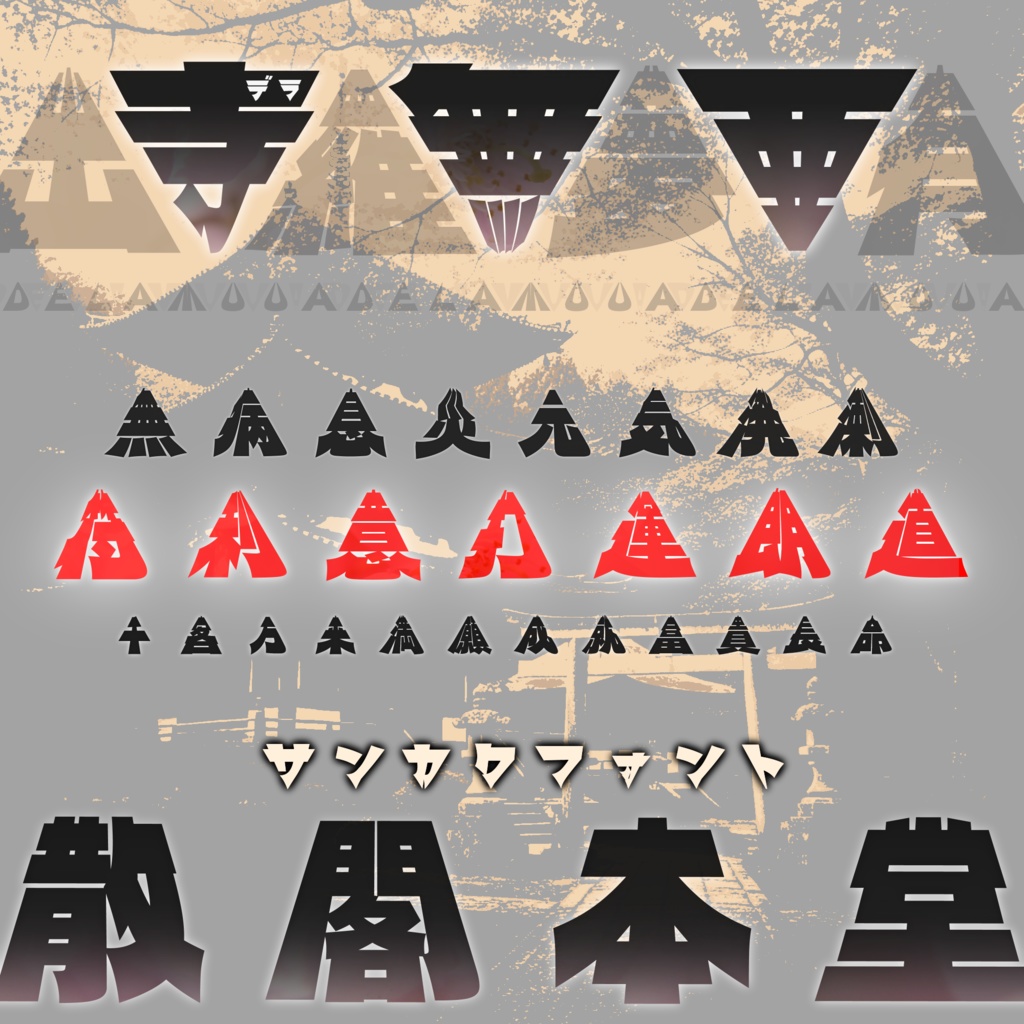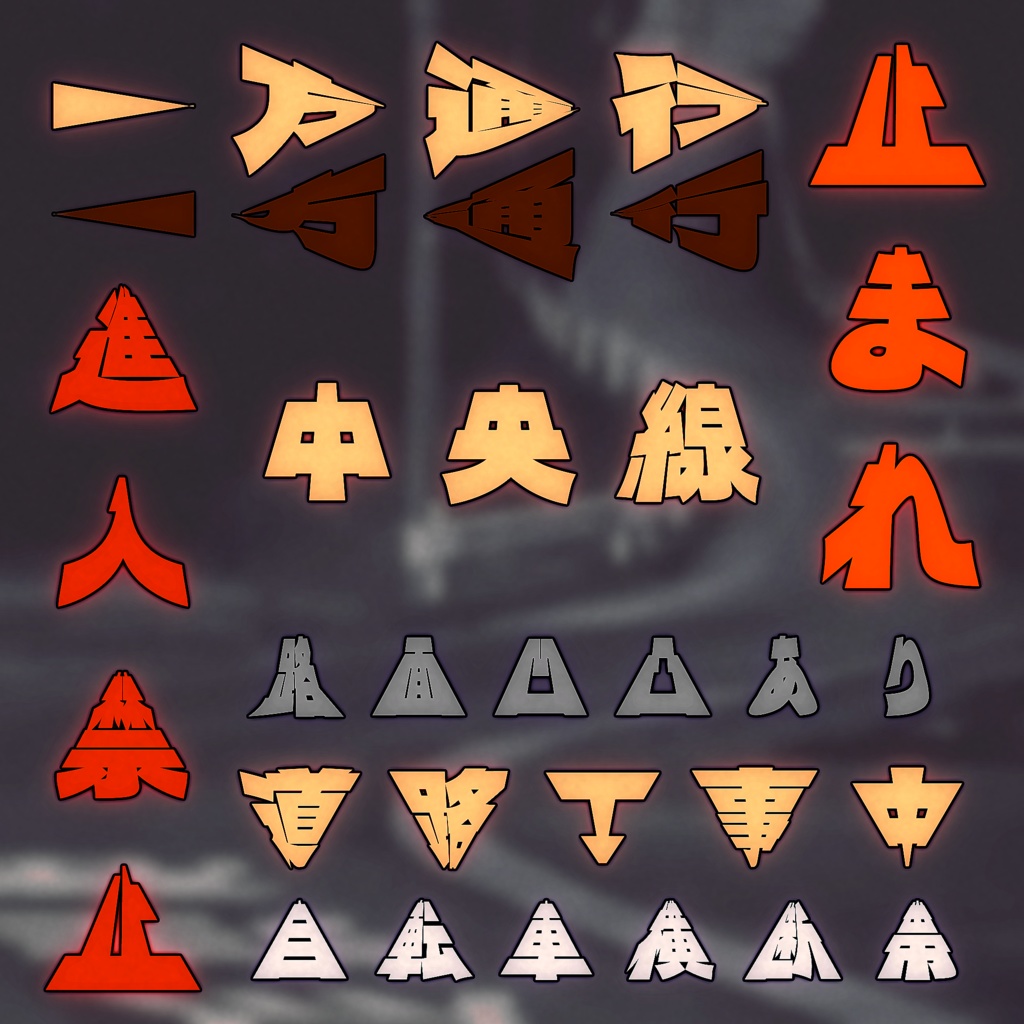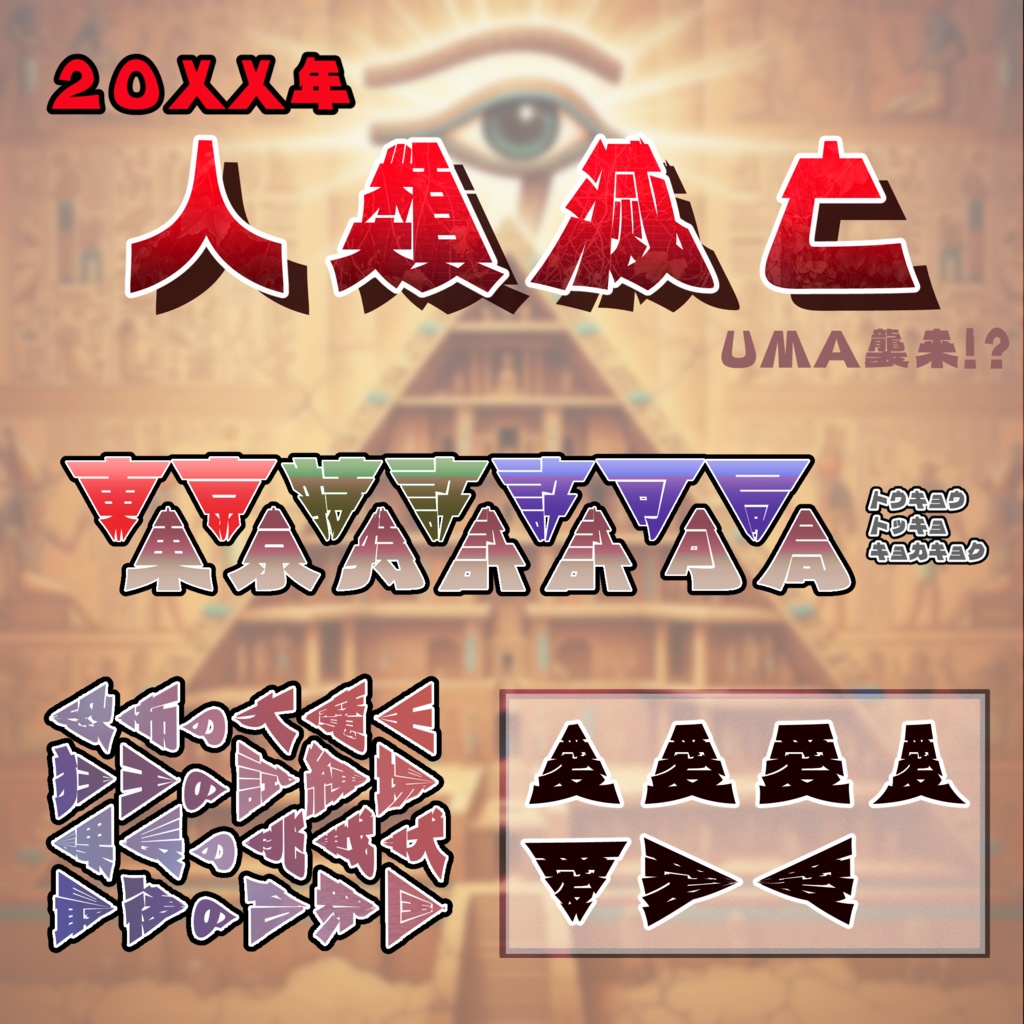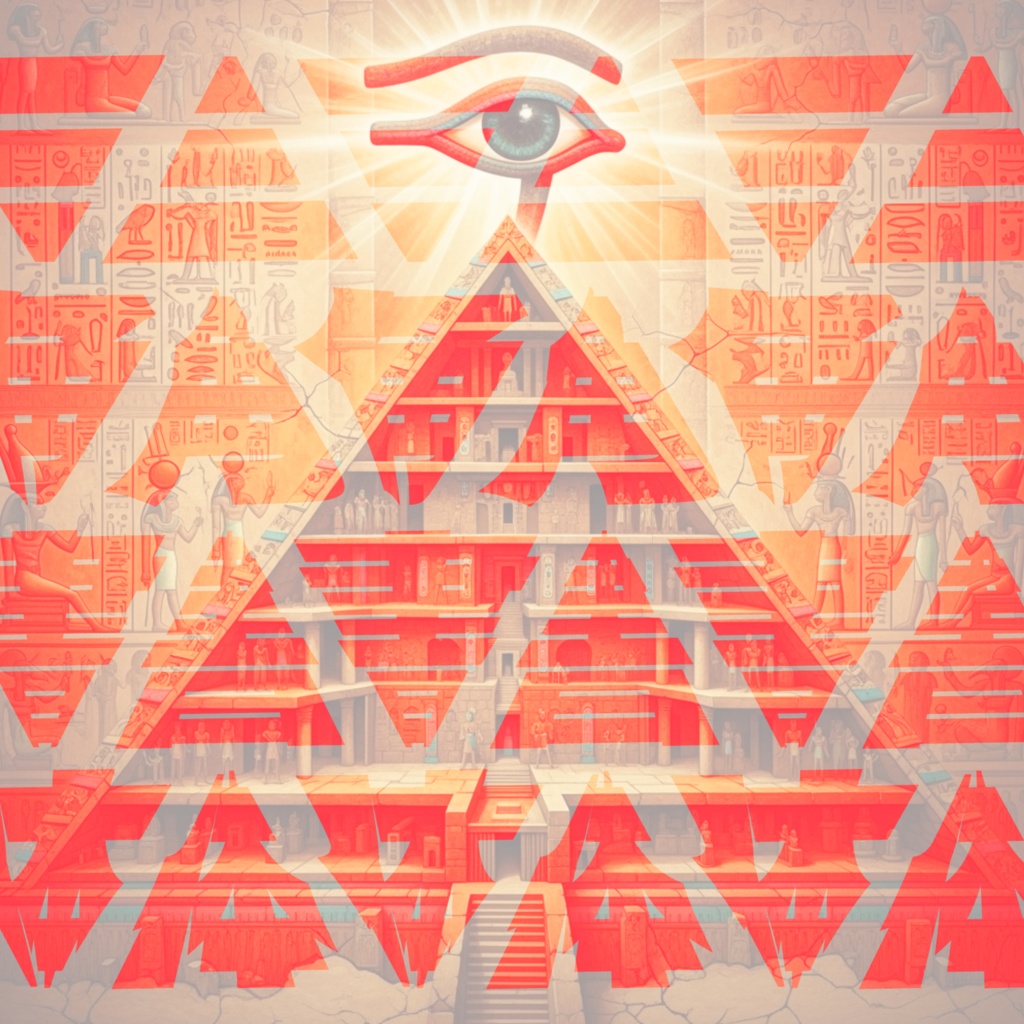
三角書体『デラ・ムーア』【フリーフォント】
『デラ・ムーア』(Dela-MuuA) 三角形が刻む、新たなインパクト。 シャープな三角形のシルエットが目を引く、デザイン向けのフォントです。
● デラ・ムーア 上 1 ● デラ・ムーア 上 2 ● デラ・ムーア 上 3 ● デラ・ムーア 上 4 ● デラ・ムーア 下 ● デラ・ムーア 左 ● デラ・ムーア 右 尖りの方向や鋭さが異なる、合計7種類のフォントを同梱。 「上1〜3」と「下」が使いやすくおすすめです。
本フォントは、オープンソースフォント 『デラゴシック』(Dela Gothic One) https://github.com/syakuzen/DelaGothic をベースに、独自の加工と調節を施して制作しました。素晴らしいフォントを公開してくださった制作者様に心より感謝申し上げます。 【ご使用上の注意点】 漢字のデザインを優先して制作したため、ひらがな、カタカナ、英数字などの一部の文字において、デザインの粗さや調整が不十分な点が見られる場合がございます。 あらかじめご了承の上、デザインのアクセントとして当フォントをご活用いただけますと幸いです。